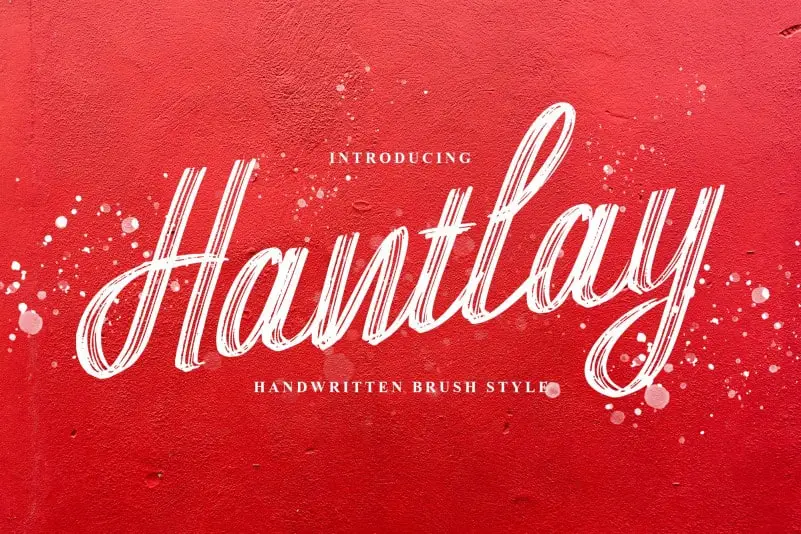
Hantlay Brush Font – Download Grátis
A Hantlay Brush Font é uma fonte de texto feita para quem busca um charme natural na tipografia. Ela foi criada com a ajuda de um canetão, resultando numa textura única e vibrante que parece ter sido feita à mão por alguém de uma bela arte culinária ou artesanato. Esta fonte se destaca em projetos de marcação, logomarca, design de casamento, postagem no mídia social, anúncio, embalagens de produtos, design de produto, etiquetas e até mesmo na fotografia e nas marcas de água da foto. Sua textura suave e sua elegância perfeita para qualquer projeto que você possa imaginar, seja ele uma criação visual ou tipográfica, tornando-a um recurso indispensável em qualquer tipo de trabalho criativo. A Hantlay Brush Font é ideal para quem busca transmitir uma mensagem autêntica através da forma e do texto, com a delicadeza de uma mão artesanal queima o papel no momento preciso.